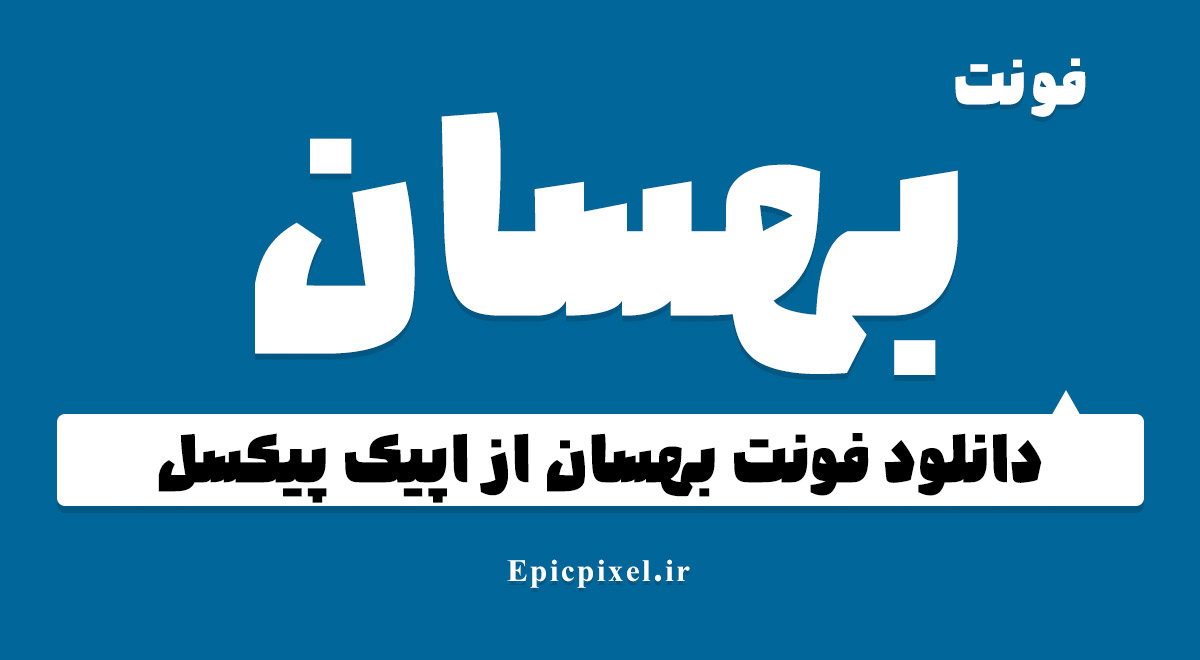
| ⭐ توضیحات | مجموعه ای کامل از فونت های بهصان و نسخه شبیه سازی شده اپیک بهسان فونت اپیک بهسان با پشتیبانی از حروف فارسی و انگلیسی (لاتین) ، اعداد فارسی Fu Num و انگلیسی بهمراه نسخه وب |
فونت بهسان یک فونت فارسی زیبا و منحصر به فرد
حالا، اگر شما دنبال یک فونت خوب برای طراحی های فارسی خود هستید، ما به شما یک پیشنهاد داریم: فونت بهسان.
فونت بهسان یکی از زیباترین و منحصر به فردترین فونت های فارسی است که توسط حسین زاهدی طراحی و پیاده سازی شده است. این فونت از سری فونت های ضخیم و دکوراتیو می باشد که برای عناوین و تاکید مناسب است. این فونت دارای قطعات جذاب و خلاقانه ای است که حروف را به هم متصل می کند و یک جریان هماهنگ و زنده را ایجاد می کند.
معرفی فونت بهسان
فونت بهسان یک فونت فارسی است که در سال 1401 طراحی و پیاده سازی شده است.
فونت بهسان یک فونت نمایشی است که برای عناوین و لوگو مناسب است. این فونت دارای حروف بزرگ و ضخیم است که با قطعات دکوراتیو به هم متصل شده اند. این قطعات باعث می شود حروف گیرای تر و جذاب تر به نظر برسند. همچنین این قطعات با رعایت قوانین خط نستعلیق، حروف را به صورت پلکانک شکل میدهد.
خصوصیات فونت بهسان
فونت بهسان دارای چند خصوصیات مهم است که در ادامه به آن ها اشاره می کنیم:
- قابل خواندن: این فونت با وجود دکوراسيون های زياد، قابل خواندن است. حروف به صورت روشن و واضح قابل تشخيص هستند.
- سازگار: اين فونت با محتوای مورد نظر شما همخواني دارد. اگر شما قصد داريد يك عنوان يا يك لوگو بسازيد، اين فونت مي تواند به شما كمك كند تا طراحي خود را زيباتر و جذاب تر كنيد.
- منحصر به فرد: اين فونت داراي شخصيت و شكل خود است. اين فونت با هيچ فونت ديگري شباهت ندارد و مي تواند براي برند سازي و ايجاد حس اختصاصي مفيد باشد.
کاربردهای فونت بهسان
فونت بهسان يك فونت نمايشي است كه براي عناوین و لوگو مناسب است. اما اين به اين معني نيست كه شما نمی توانید از این فونت در سایر زمینه های طراحی گرافیک استفاده کنید. بلکه شما می توانید با خلاقیت و تجربه خود، از این فونت در طراحی های مختلفی استفاده کنید. برخی از کاربردهای ممکن فونت بهسان عبارتند از:
- طراحی پوستر، بروشور، کارت ویزیت، فلایر، بنر و …
- طراحی لوگو، نشان تجاری، علامت و …
- طراحی جلد کتاب، مجله، روزنامه و …
- طراحی تی شرت، کیف، لیبل و …
- طراحی دعوت نامه، کارت تبریک، کارت عروسی و …
البته این فقط بخشی از کاربردهای ممکن فونت بهسان است. شما می توانید با تست و آزمایش، کاربردهای جدید و جالب دیگری را برای این فونت پیدا کنید.